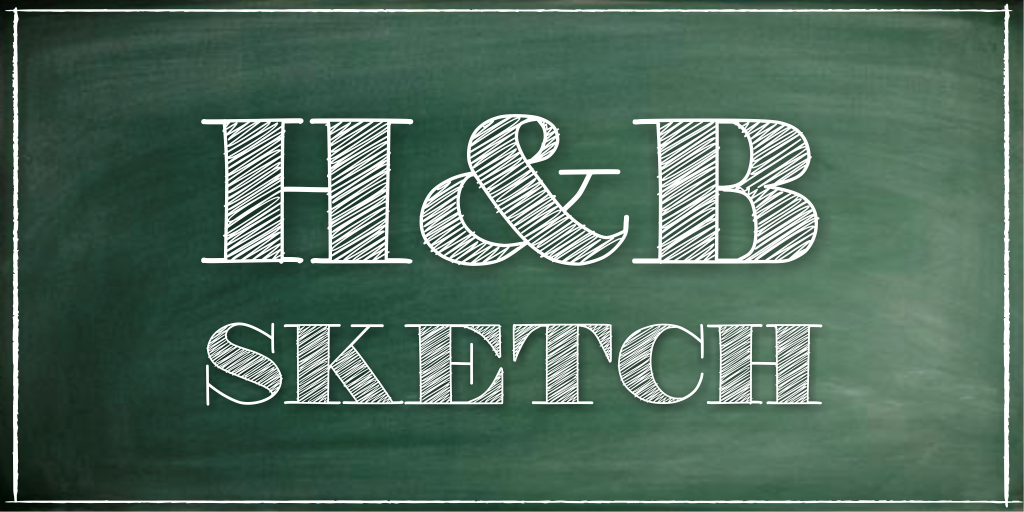
A fonte H&B Sketch Font é uma sugestão perfeita para arquitetura de interiores moderna ou decoração minimalista. Inspirada no estilo artístico, a fonte traz um tom suave e elegante ideal para criações decorativas. Seu design minimalista, combinado com linhas leves e detalhes sutis, é perfeito para adicionar um toque autêntico ao seu trabalho de gráfica. Se você está procurando por uma fonte que ofereça tanto estilo quanto funcionalidade, H&B Sketch Font pode ser sua escolha certa. Focado na elegância moderna e no design minimalista, a fonte é ideal para criar nomes e rótulos que se destacam sem demarcar. Para usuários atentos à qualidade do produto, a Hamilton oferece uma demo limitada da fonte, com opção de teste em seu site oficial. Este teste pode ajudá-lo a garantir que H&B Sketch Font seja exatamente o que está procurando para seus projetos futuros.